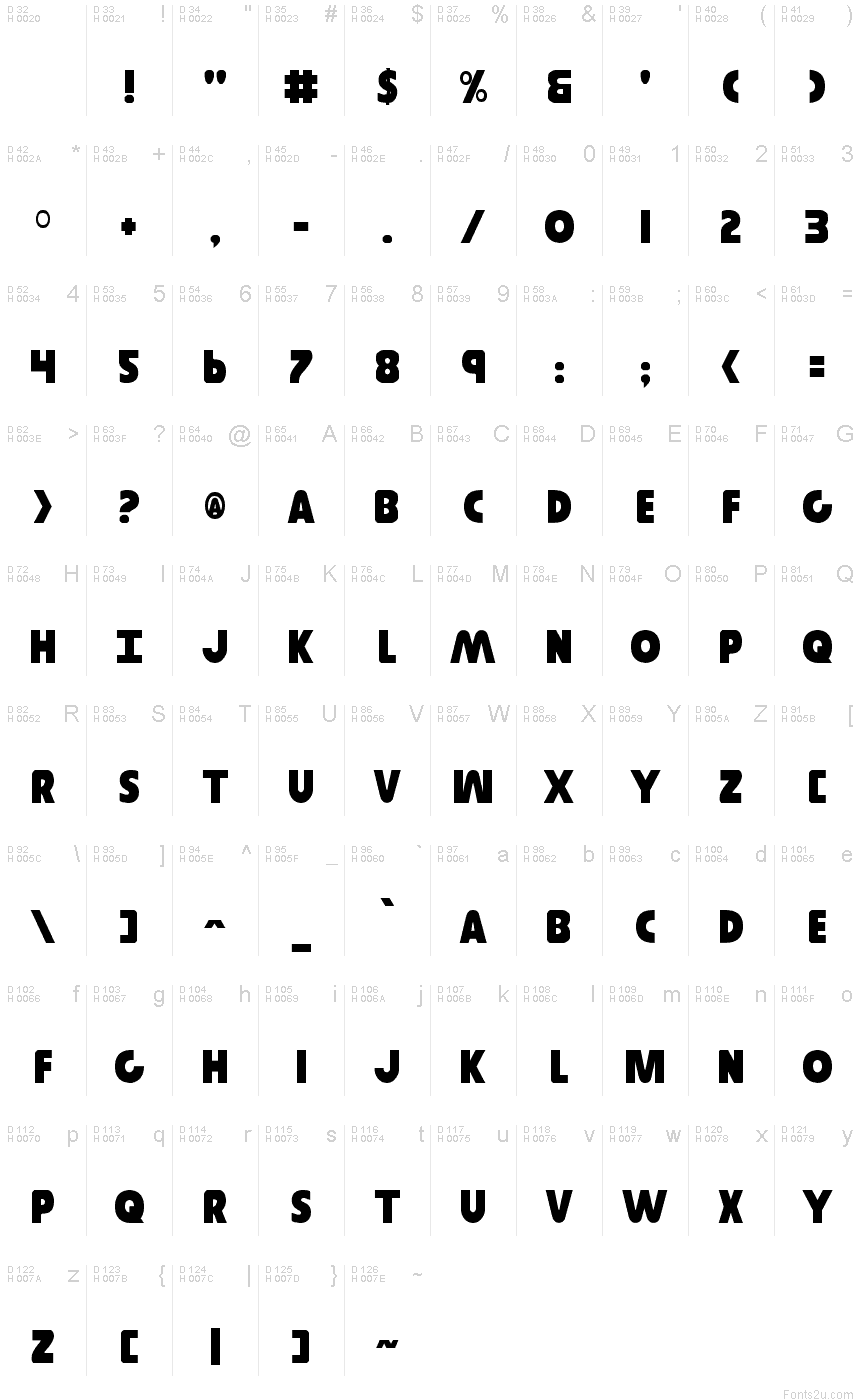
Governor
Governor von Iconian Fonts ist eine moderne, abgerundete Display-Schrift. Ihre breiten, schweren Buchstaben schwellen mit weichen Kurven an und verleihen jedem Wort eine kühne, fast aufblasbare Präsenz, die dennoch sauber und kontrolliert wirkt. Die Innenräume bleiben offen und weit, sodass der Text selbst in großen Größen geschmeidig und lesbar wirkt, anstatt plump oder gequetscht zu sein. Es liegt eine verspielte Autorität in dieser Schrift – wie bei einer Beschilderung von einem Retro-Sci-Fi-Jahrmarkt: selbstbewusst, laut und unübersehbar.
Mit Governor rasten große Titel sofort in starke, blockartige Formen ein, die Ihr Layout verankern. Diese kostenlose Schriftart glänzt auf Postern, Spiele- oder App-Logos, Produktverpackungen, auffälligen Event-Flyern und aufmerksamkeitsstarken Social-Media-Grafiken. Sie funktioniert auch hervorragend für ausgefallene Ladenschilder oder Überschriften auf Landingpages. Für eine einfache Kombination nutzen Sie Governor für Überschriften und eine leichte geometrische serifenlose Schrift für den kleineren Begleittext, um den Fokus auf diese wuchtigen, skulpturalen Formen zu lenken.